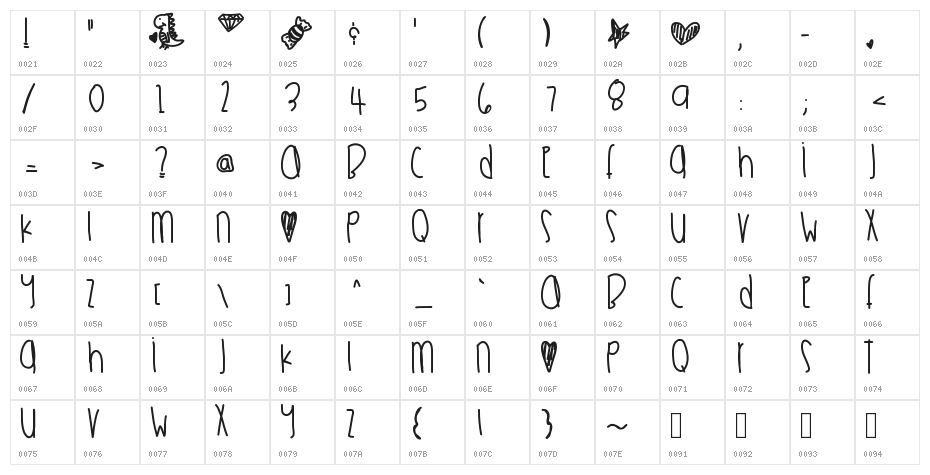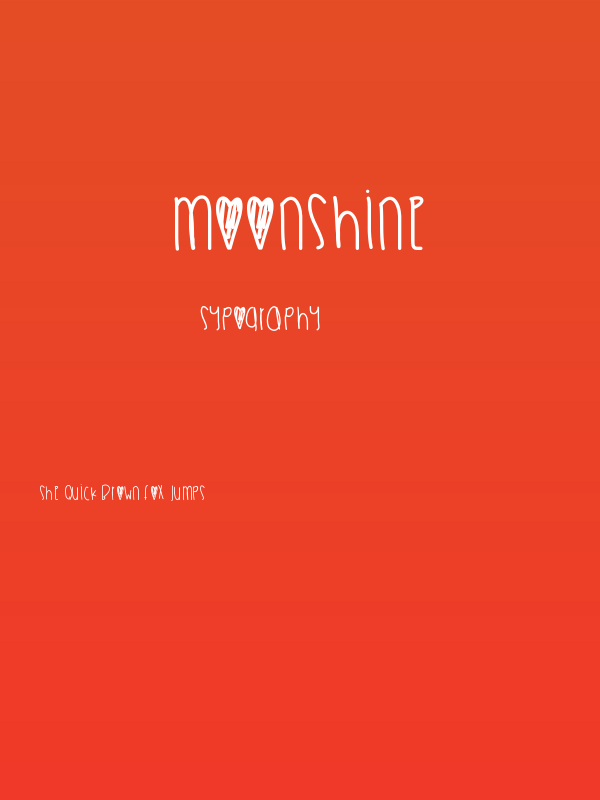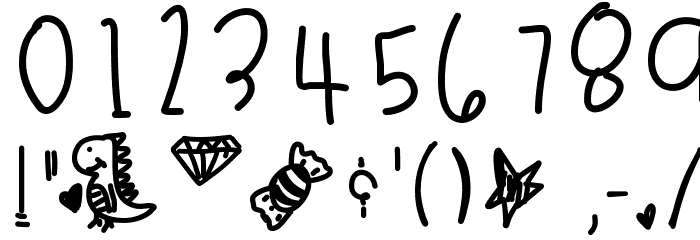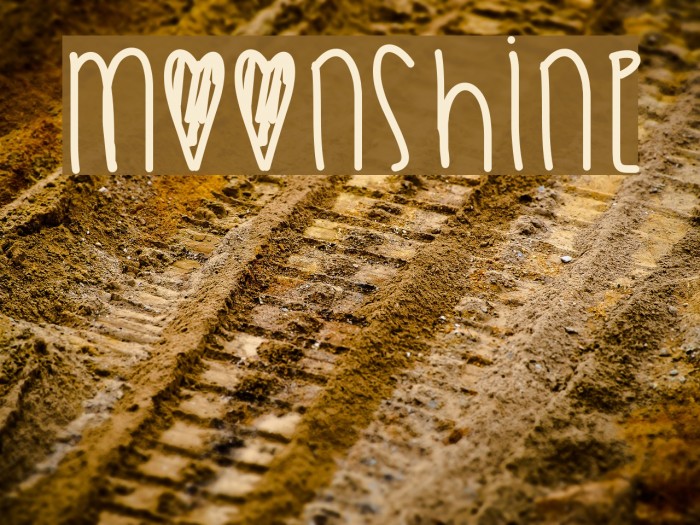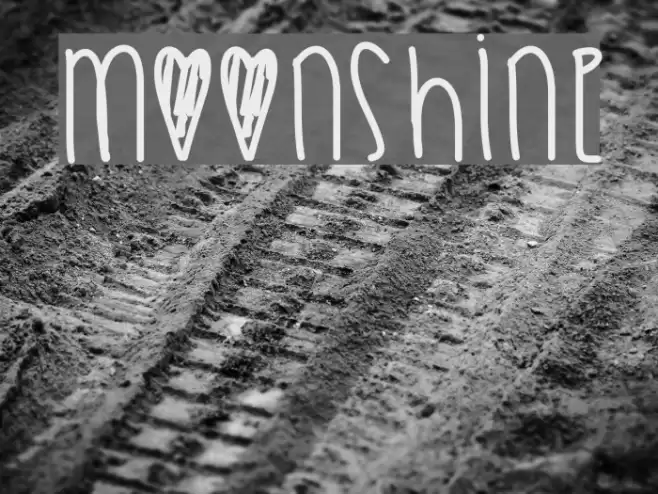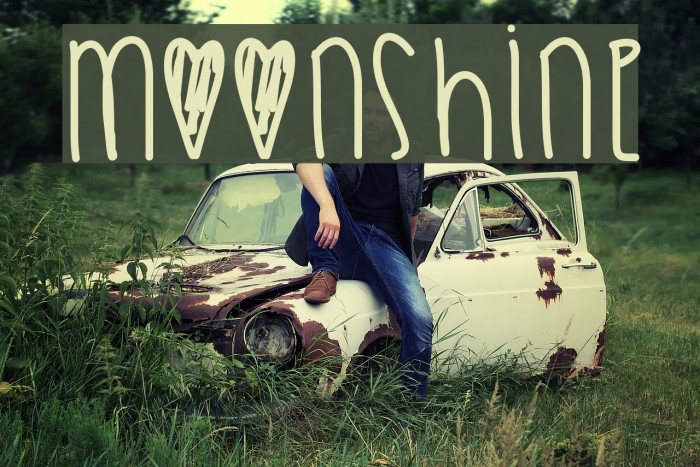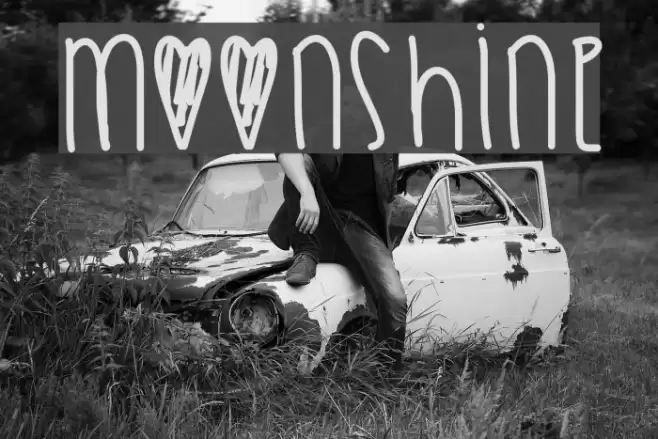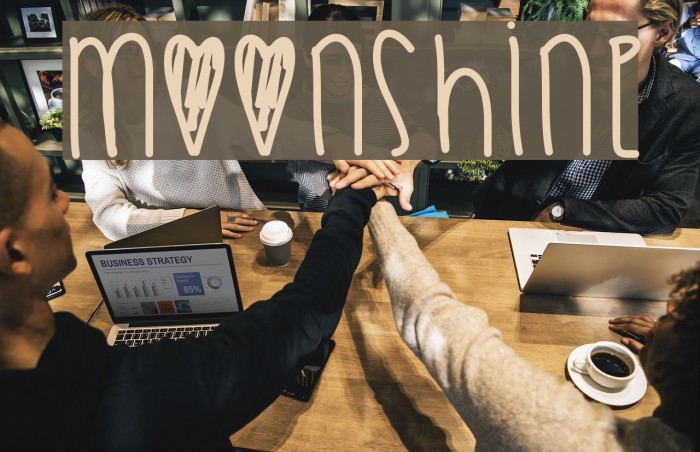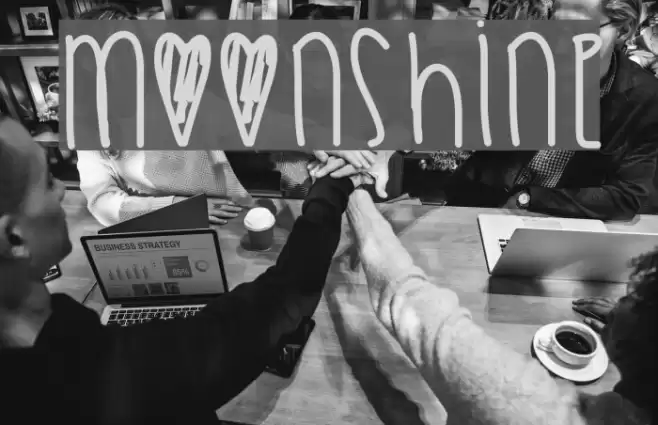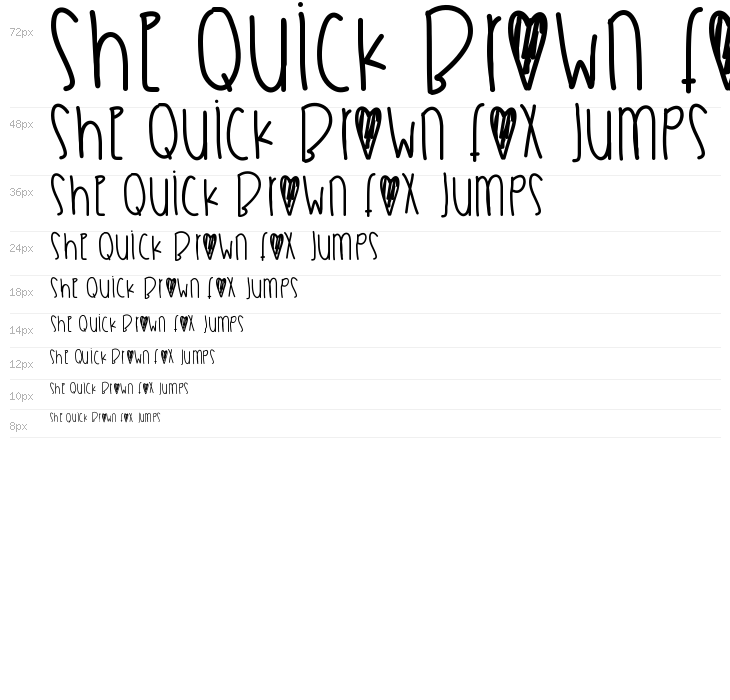
Moonshine Font
| Область применения | Headlines, Logos, Social media graphics |
| Рекомендуемые проекты | Ideal for children's books, greeting cards, playful branding, and social media graphics. |